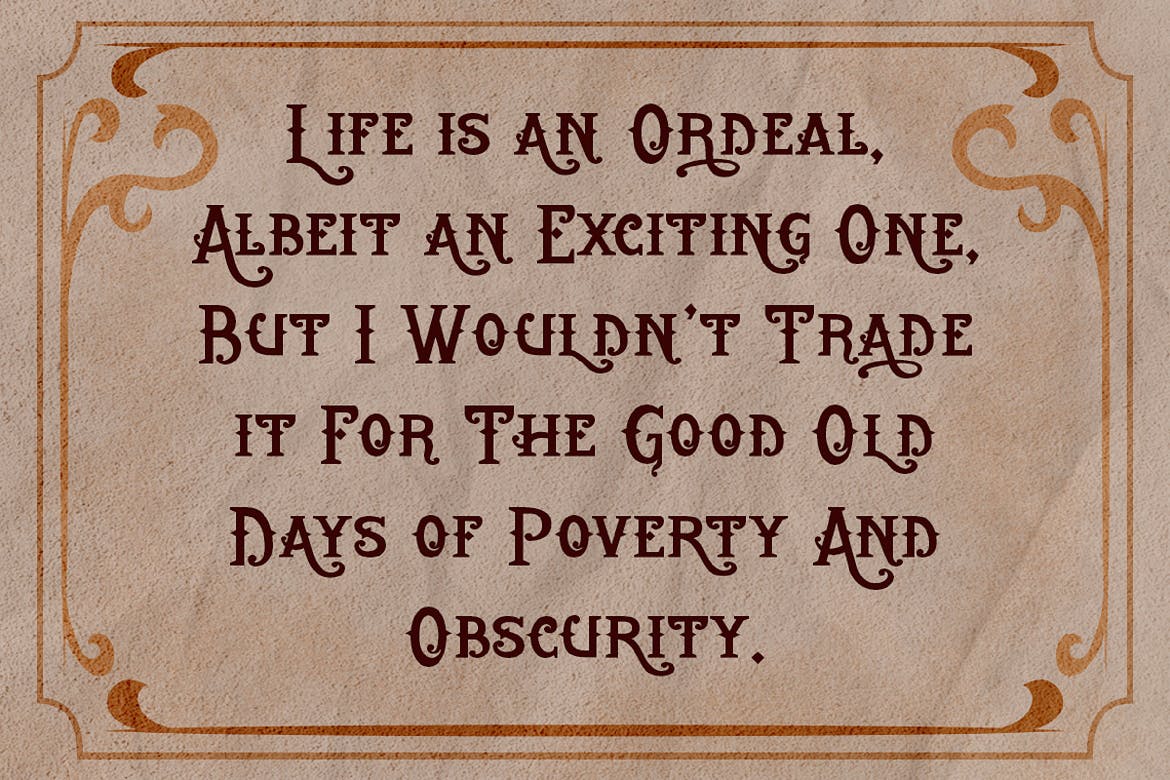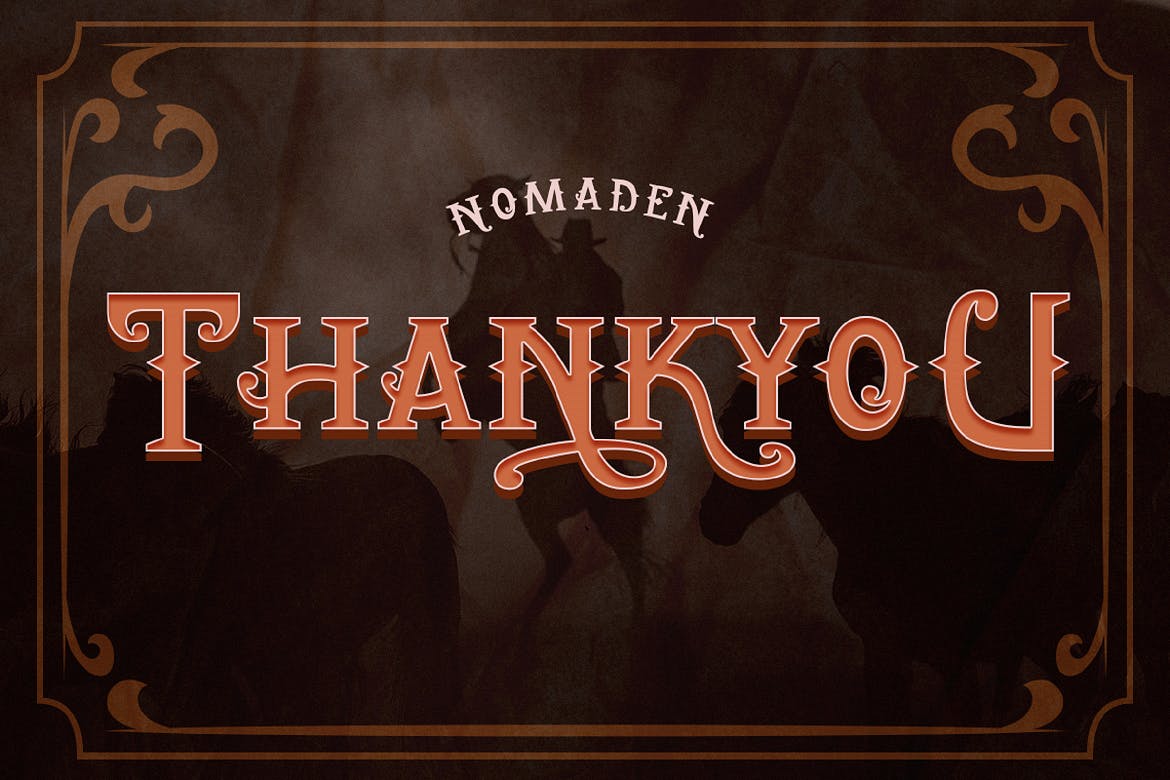
آیا به دنبال ایجاد برندی منحصر به فرد و به یادماندنی هستید؟ شاید بخواهید تبلیغاتی طراحی کنید که توجهها را جلب کند؟ یک فونت وینتیج جذاب، راهی عالی برای انجام این کار است!
معرفی میکنیم: Nomaden - یک فونت تایپفیس وینتیج.
این فونت زیبا میتواند بر روی بستهبندی، لباس، مواد چاپی و هر چیزی که برند شما نیاز دارد، عالی به نظر برسد. علاوه بر این، میتوانید از آن در وبسایتها و شبکههای اجتماعی نیز استفاده کنید و مطمئن باشید که همیشه از جمع متمایز خواهید بود.